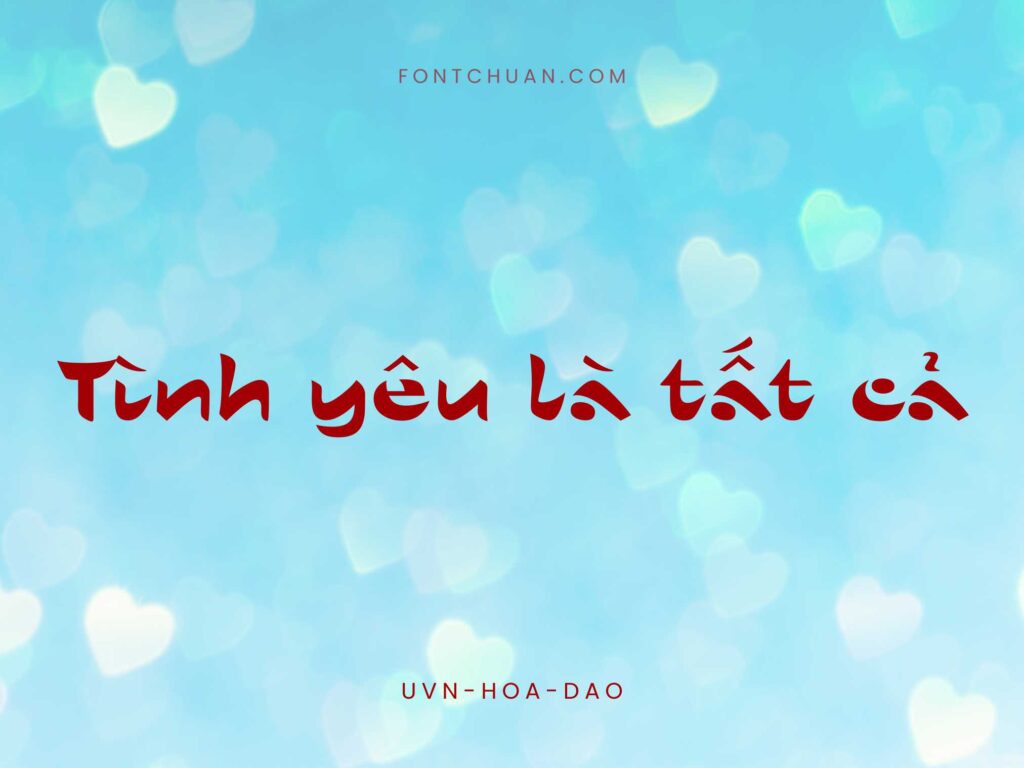
Font UVN Hoa Dao Việt Hóa
UVN Hoa Đào là một phông chữ thư pháp mang phong cách nghệ thuật viết tay truyền thống, được thiết kế bởi Tom Truong vào năm 2001. Phông chữ này có các nét bút lông mềm mại và uyển chuyển, tạo nên sự thanh thoát và tinh tế cho các tác phẩm thiết kế. UVN Hoa Đào hỗ trợ đầy đủ các ký tự tiếng Việt, giúp người dùng dễ dàng sử dụng trong các dự án sáng tạo liên quan đến văn hóa Việt Nam.
Với thiết kế độc đáo và nghệ thuật, UVN Hoa Đào phù hợp cho các ứng dụng như thiệp mời, tiêu đề sách, thiết kế logo và các ấn phẩm nghệ thuật. Trong lĩnh vực sự kiện, phông chữ này có thể được sử dụng trong các dịp như lễ hội, lễ cưới và các sự kiện văn hóa. Ngoài ra, UVN Hoa Đào còn là một Font chữ ảnh cưới lý tưởng, mang đến sự tinh tế và trang nhã cho các album cưới, thiệp cưới và các sản phẩm lưu niệm đặc biệt. Font này cũng thích hợp cho các ngành nghề như thiết kế đồ họa, nghệ thuật trang trí và xuất bản.